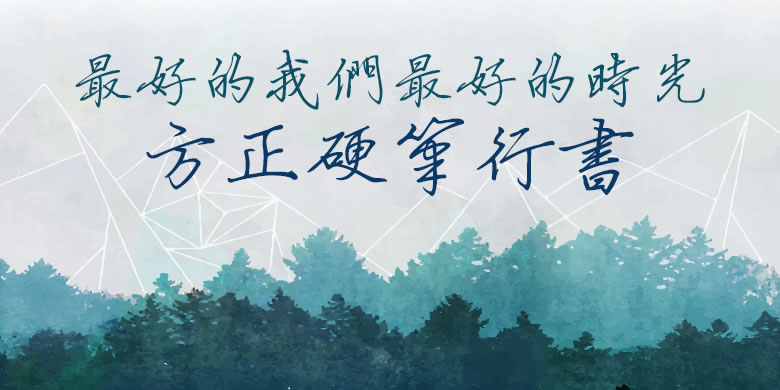
品牌:方正字库设计师:阎锐敏发行时间:2003字库编码:大陆简体(GB2312-80)、大陆繁体(GB12345-90)、简繁扩展(GBK)、港台地区(BIG-5)分类:常规书写·硬笔
方正硬笔楷书由书法家阎锐敏先生创作。这款字体笔致刚健迅捷,强调抑扬顿挫,中宫极为紧凑,外围舒展开张,整体有强烈的节奏感和速度感。其风格热情奔放,适用于现代诗歌、短文的排版以及文化、商业类品牌的广告语设计。